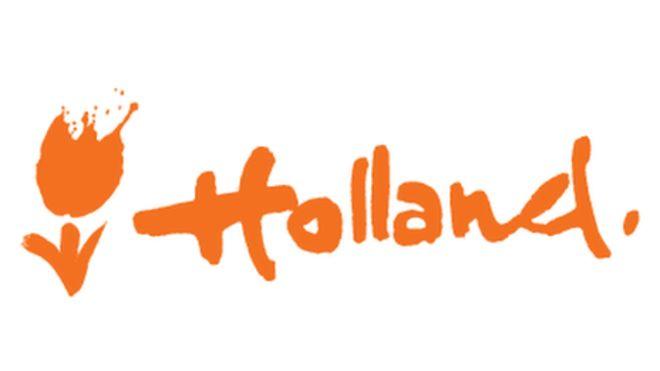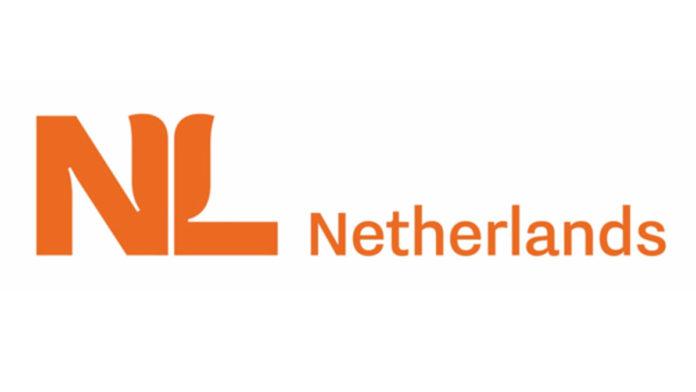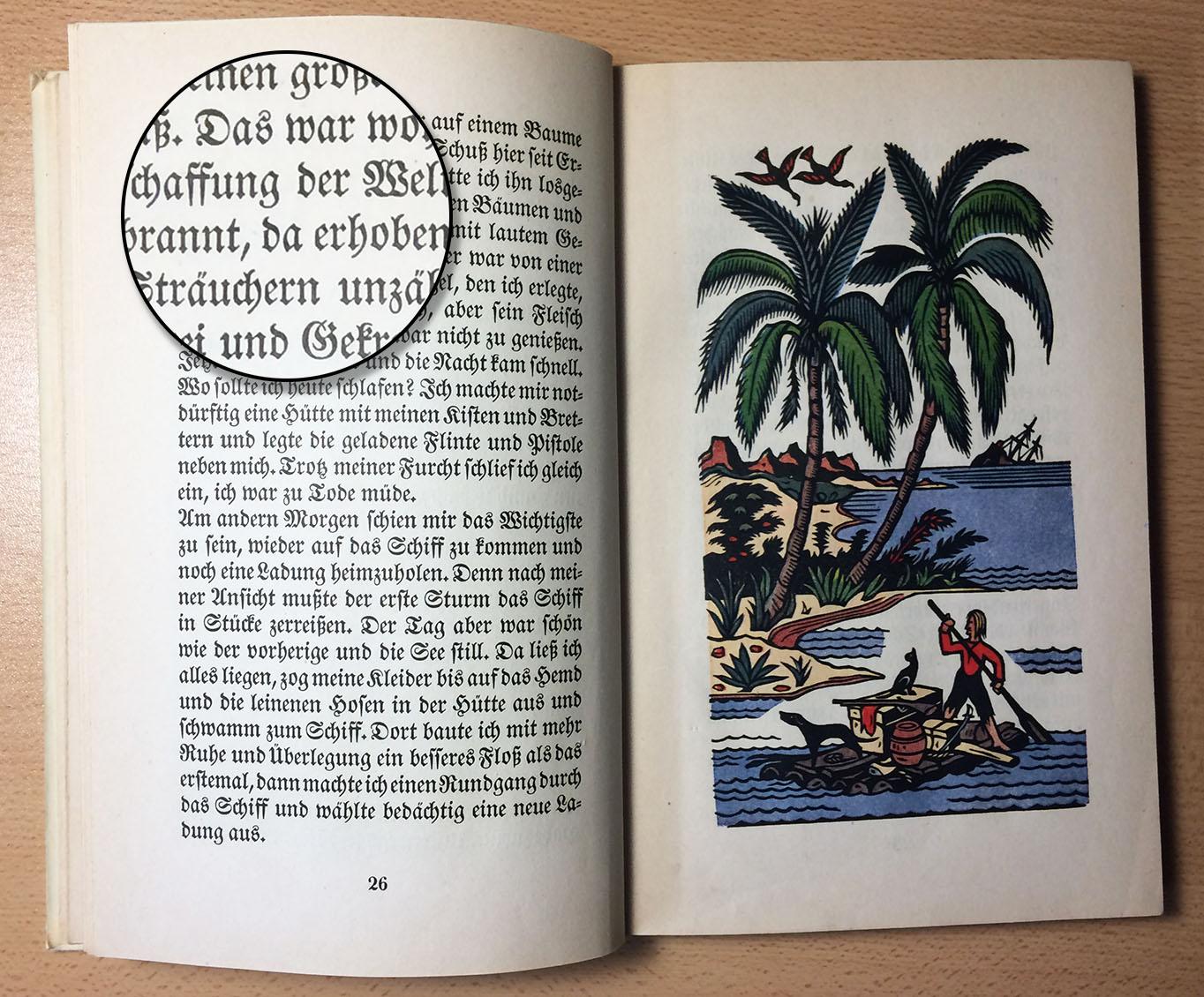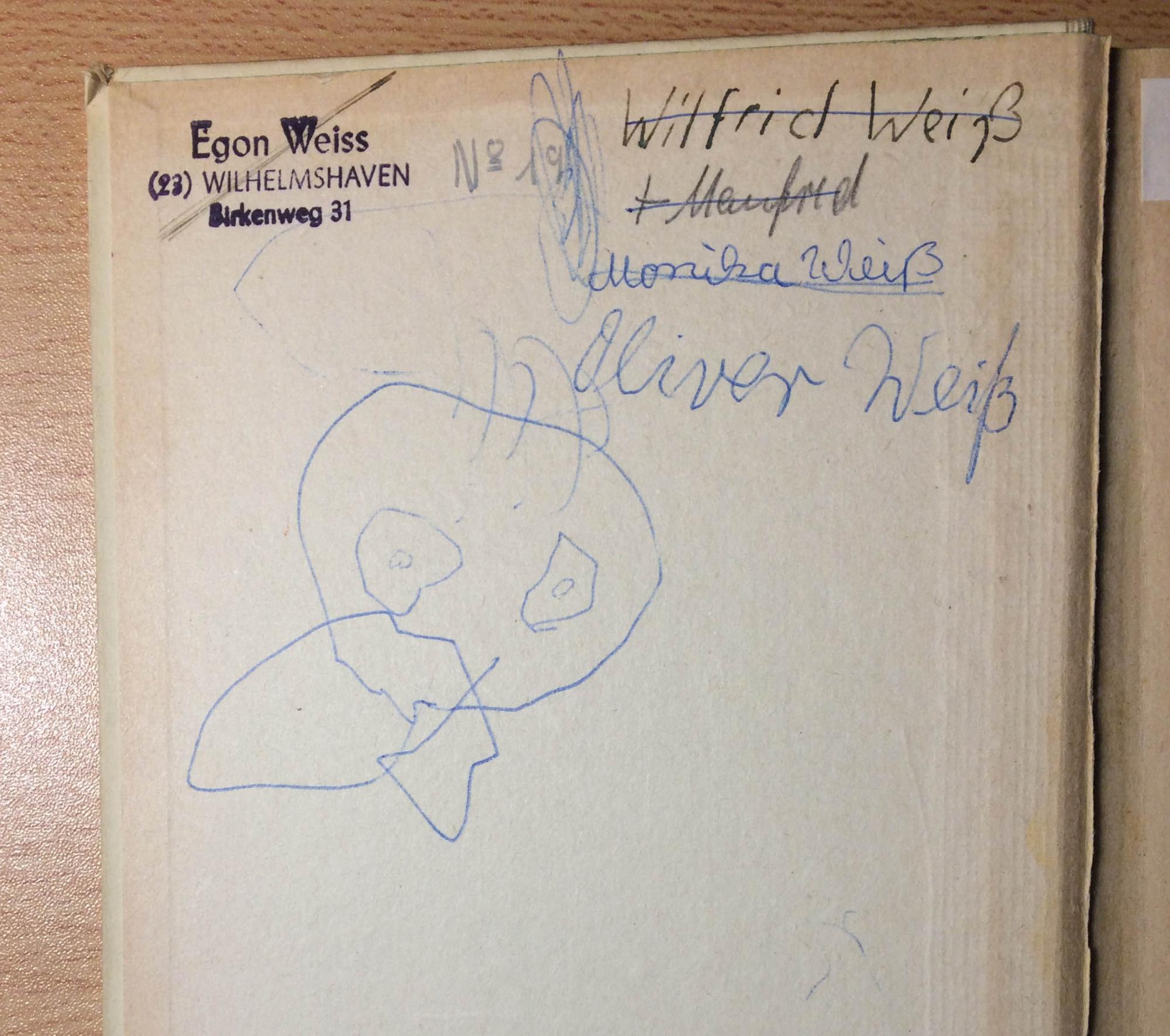
Pünzlein wechsle dich ...
Die a-Punze ist eine Schale Kaffee und die e-Punze ist der Spritzer Milch, den viele hier so gern in ihrem Kaffee haben. ;-)
Alle achten so intensiv auf die beiden armen Punzen ...
Aber wo ist eigentlich die 2. e-Punze samt ihrem e?
Hat sich das 2. e verdrückt, weil es keinen adäquaten Punzentauschpartner fand, und hat nur den Punkt als Platzhalter zurückgelassen?
Beim Aufräumen geriet mir gerade meine Kopie des "Robinson" in die Hände, die in einer kräftigen Fraktur gedruckt ist und viele schöne Holzstiche enthält.
Der Deckel bezeugt eine 80 Jahre währende Leserschaft. Mein Name, von meiner Großmutter geschrieben, war mir wohl nicht deutlich genug und bedurfte eines Konterfeis...
Hier ist die bisherige Version zum Vergleich:
Der graue Verlauf scheint übrigens nicht Teil des neuen Logos zu sein:
Niederländer selbst sehen die Holland–Niederlande-Verwirrung übrigens selbst sehr gelassen. Seit ein paar Jahren haben wir niederländische Freunde aus der Provinz  Gelderland, also eben weder aus Noord- noch Zuid-Holland. Es kam, wie es kommen musste: die hyperkorrekten Deutschen sprechen immer von den Niederlanden, Niederländern und dem Nierderländischen; die Gelderländer bezeichnen sich aber selbst als Holländer.
die hyperkorrekten Deutschen sprechen immer von den Niederlanden, Niederländern und dem Nierderländischen
Kaasköppe
:hammer:
Ich hab Verwandtschaft in Friesland und fand die Bezeichnung »Holland« für die Niederlande immer irritierend.
Friesland hat zudem die hübscheren Blumen in der Flagge ...
gelassen
Kommt darauf an. Ich kenne viele, vor allem Ex-Pats und Brabanter, die sich nicht auf Holland reduzieren lassen wollen. Und ehrlich, ich würd mich auch nicht auf Bayern reduzieren lassen wollen (Saupreiss kann ich grad eben noch akzeptieren). :blabla:
Ich finde, es dauert etwas, bis die Tulpe in voller Pracht erblüht, im Geiste ...
Das ist wie beim Kniffligen Wort, wo man die Fugen zuerstf alschs etzt ...
Das muss einem auch erst mal gefallen
Ich mag diese dezenten Logos, bei denen man erst zwei-, dreimal hinschauen muss, bis sich einem die Formensprache offenbart. Wie der Pfeil bei FedEx.
In einer Ex-Pat-Gruppe von Niederländern hatte eine die erste Wahrnehmung von "Daumenkrieg".